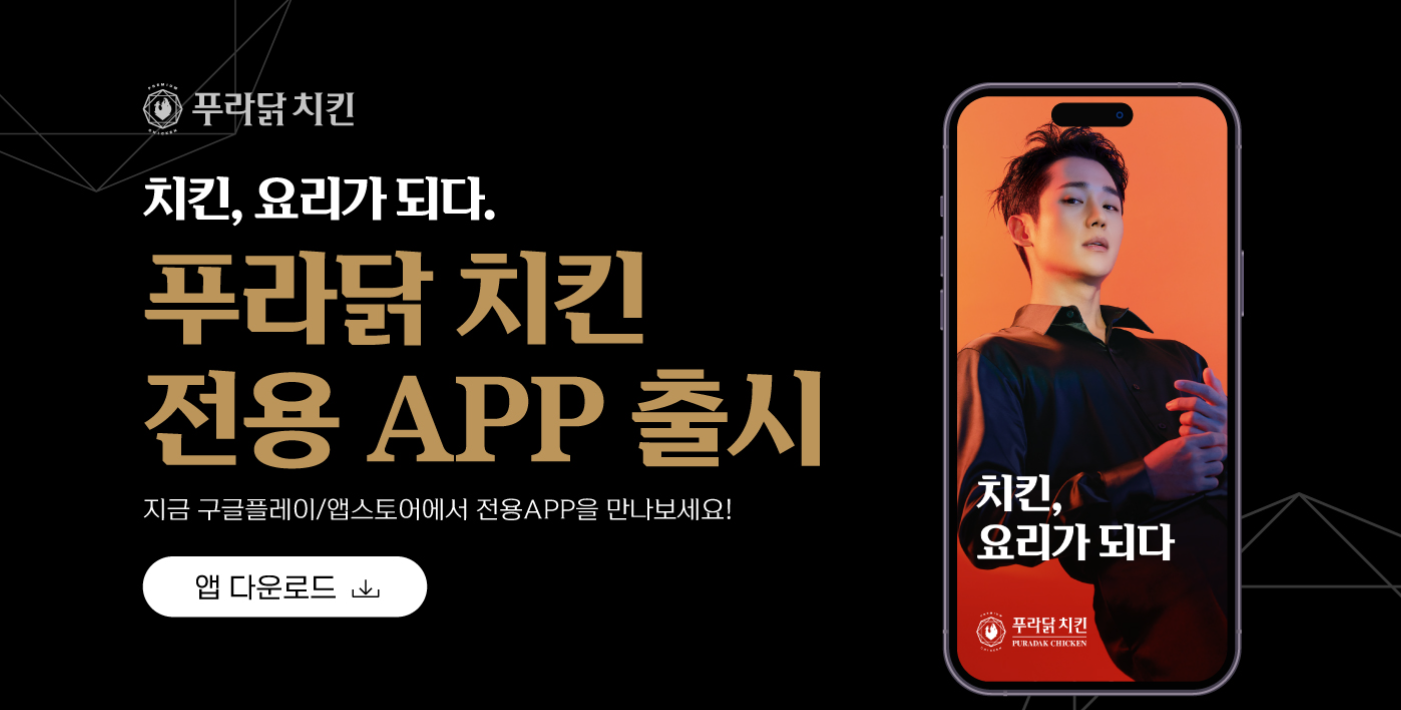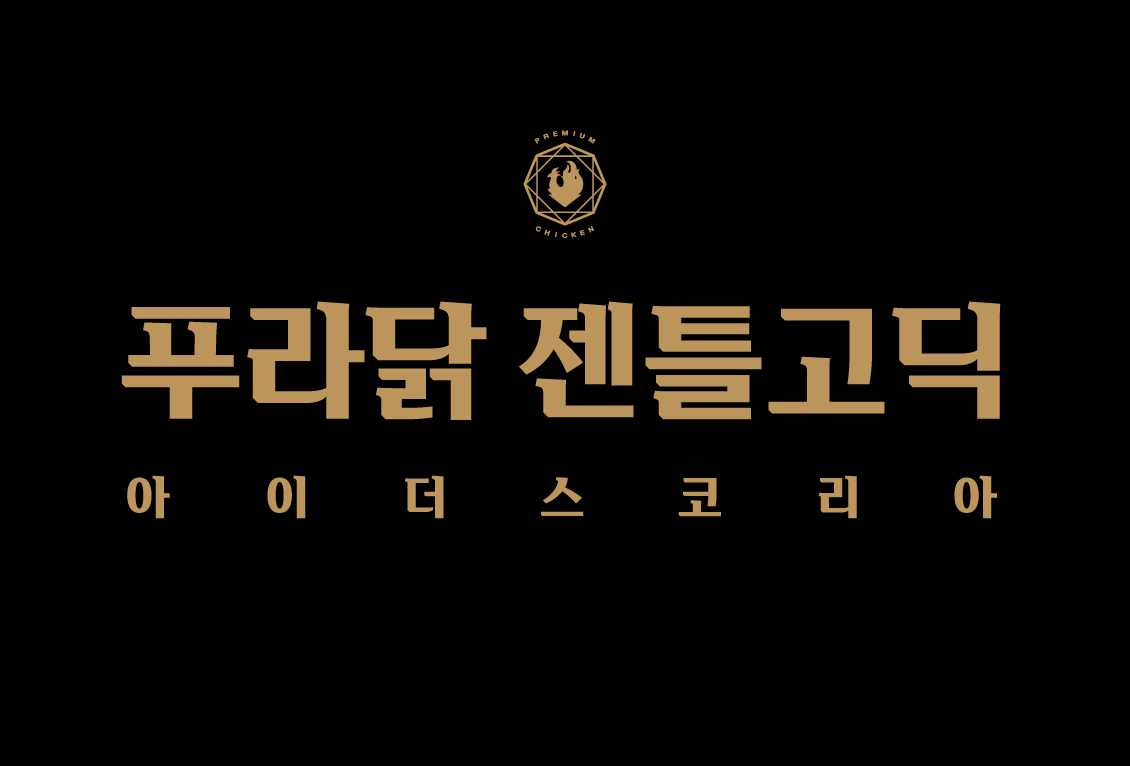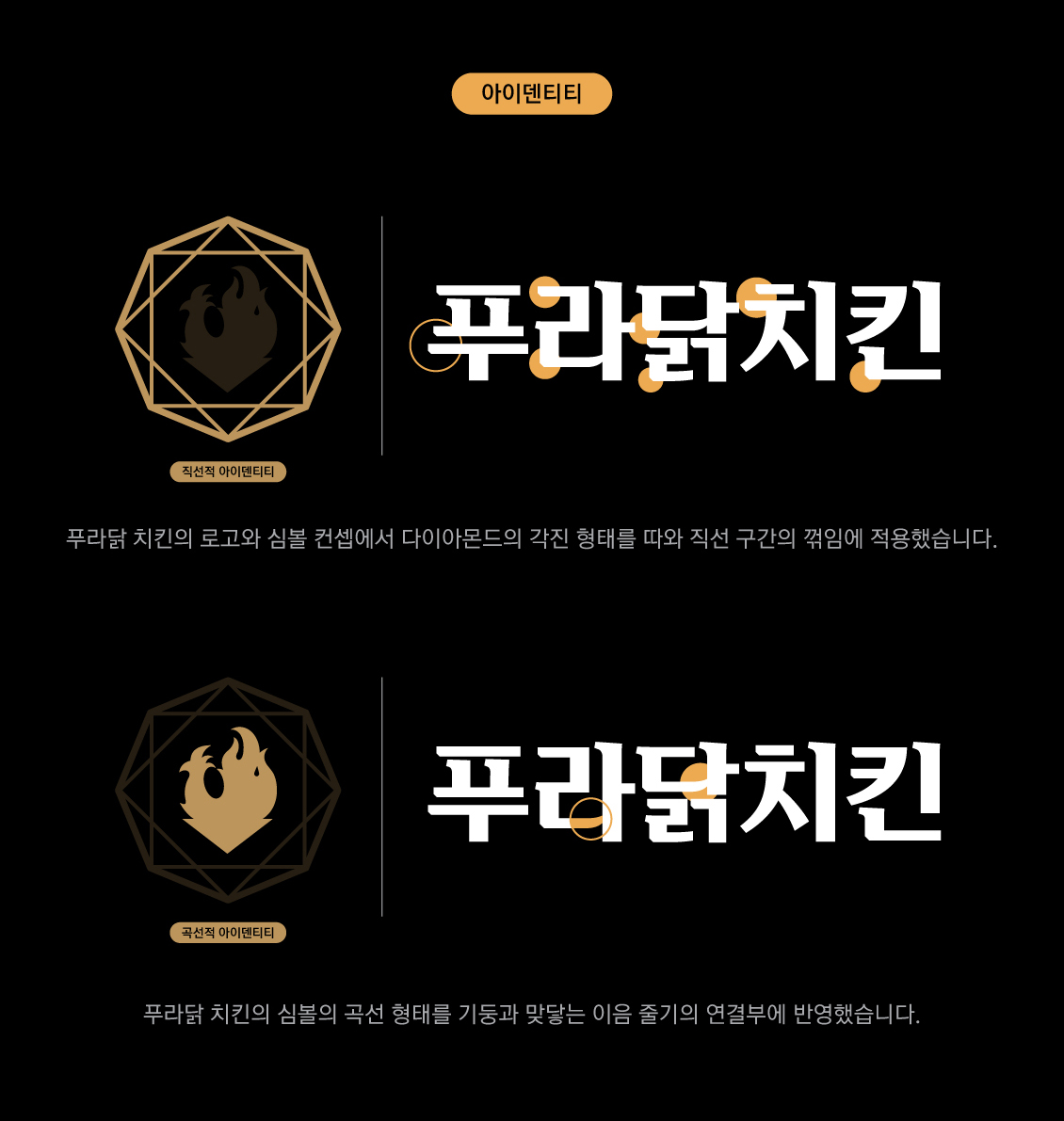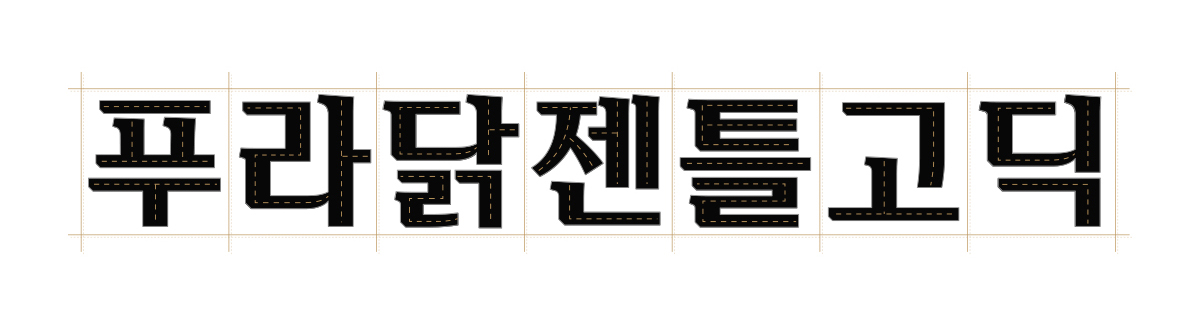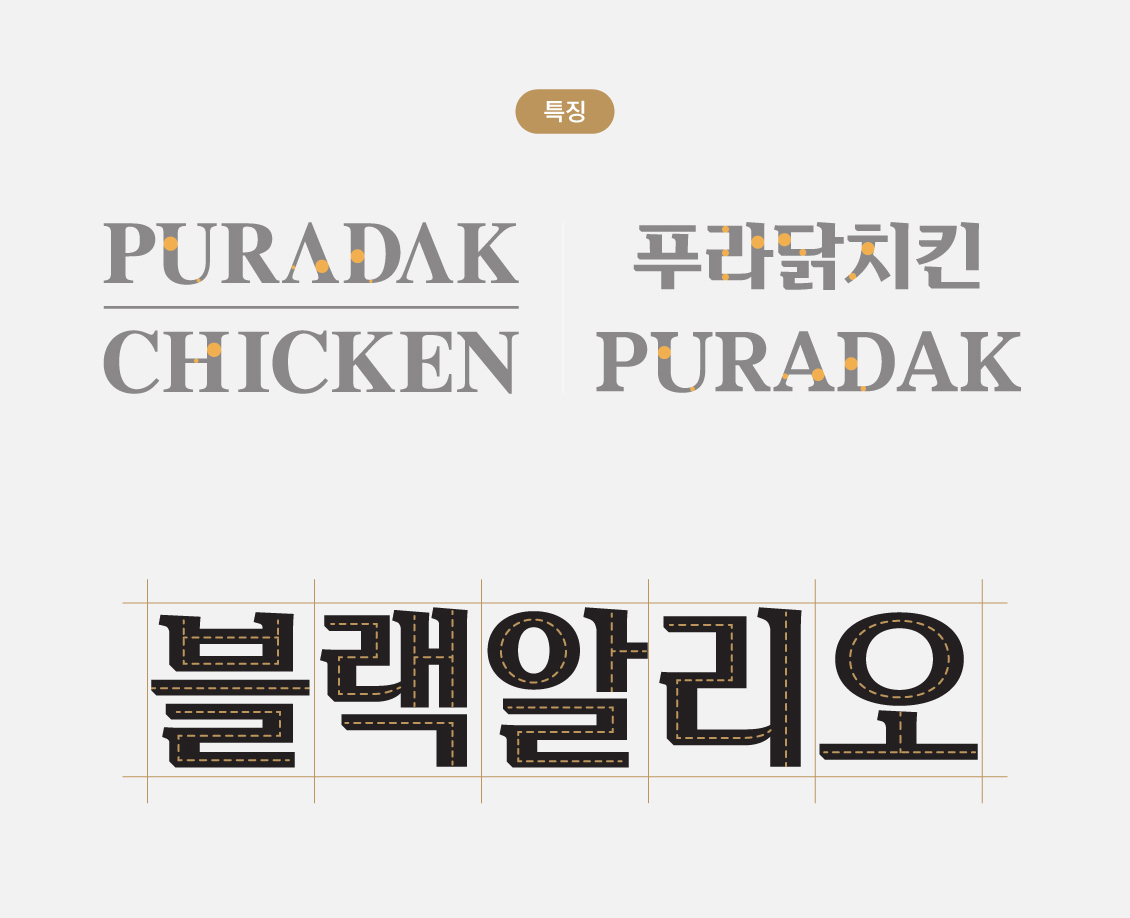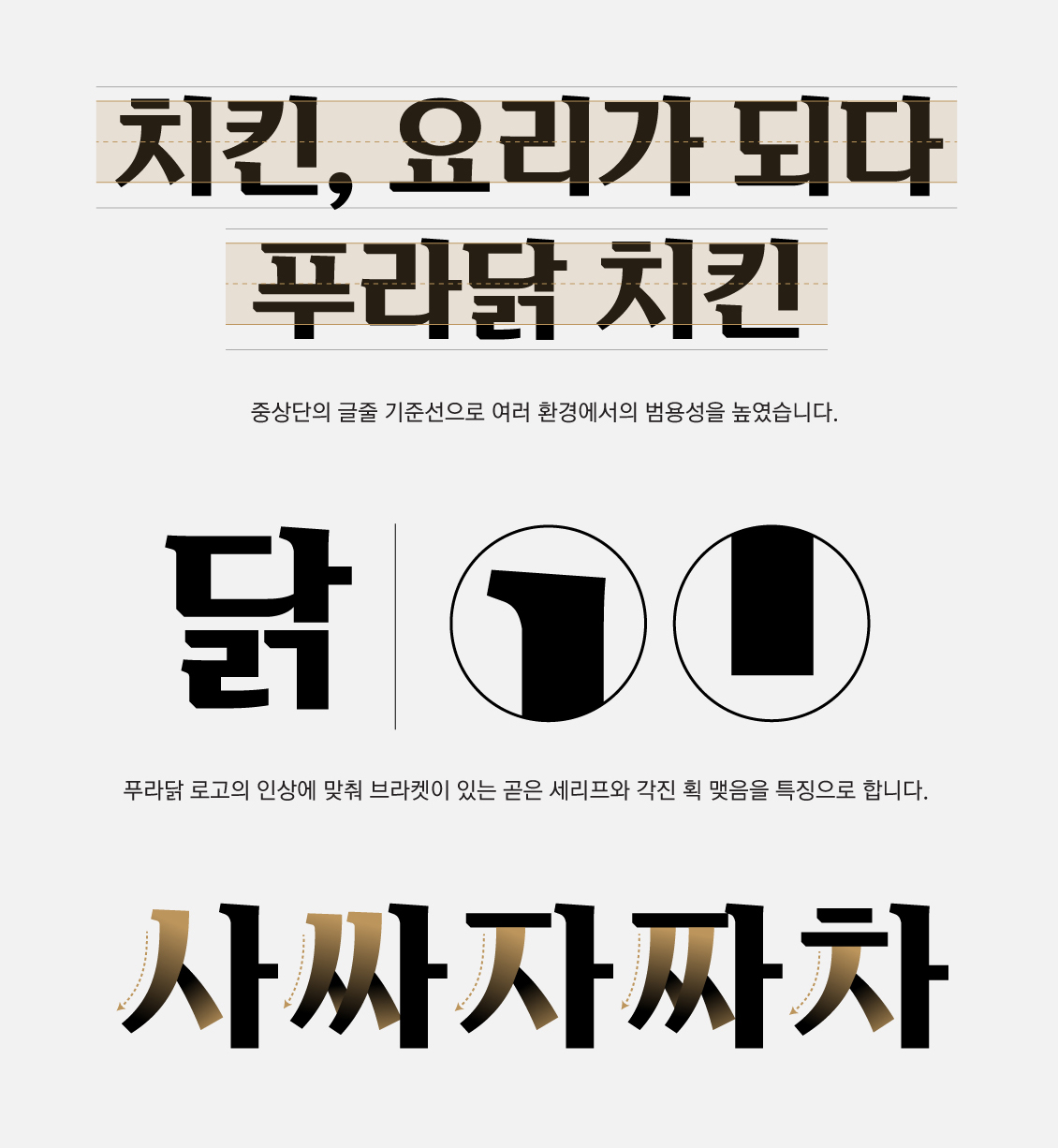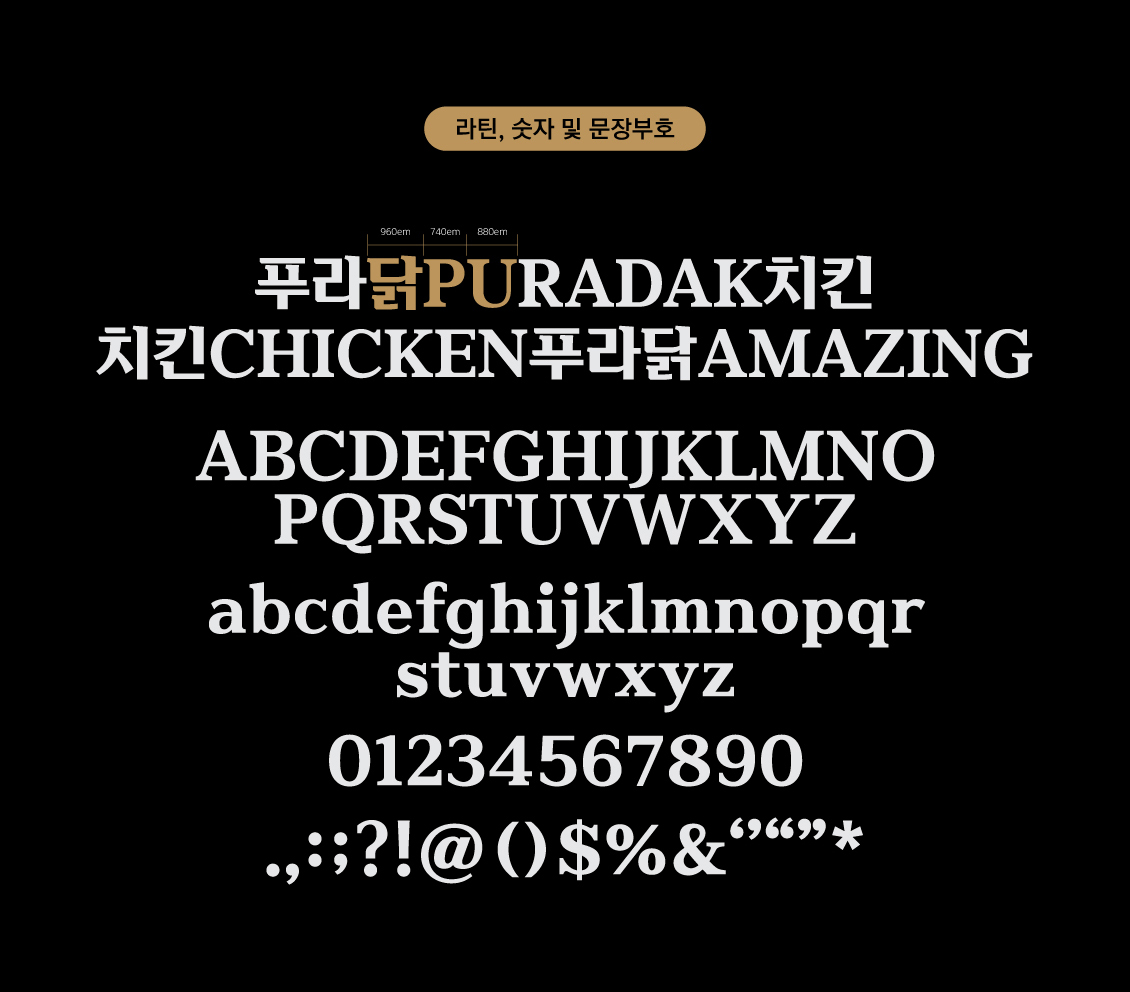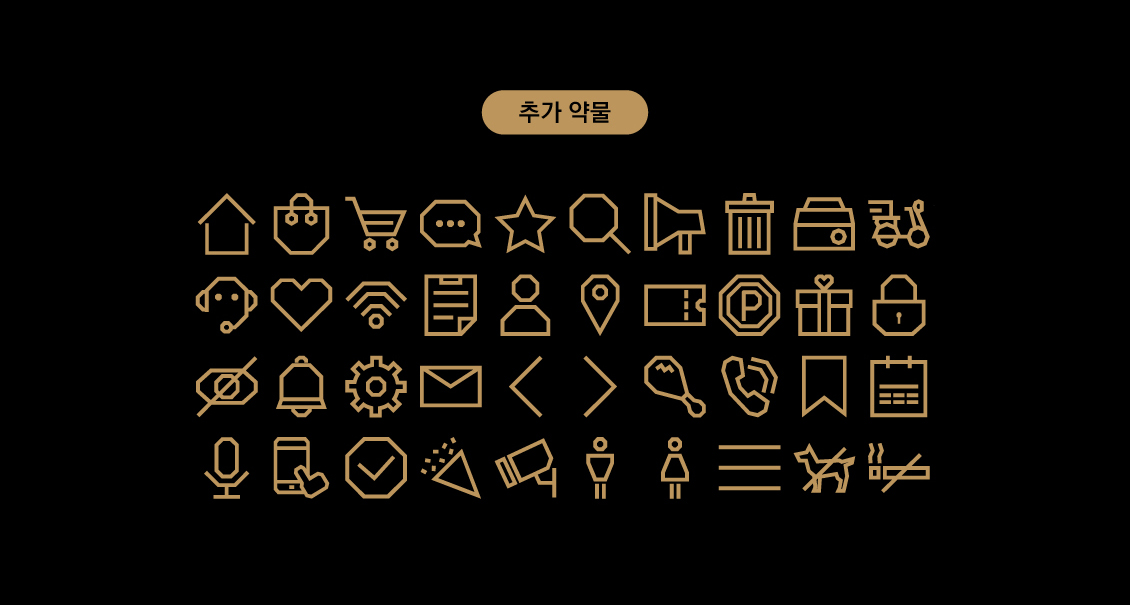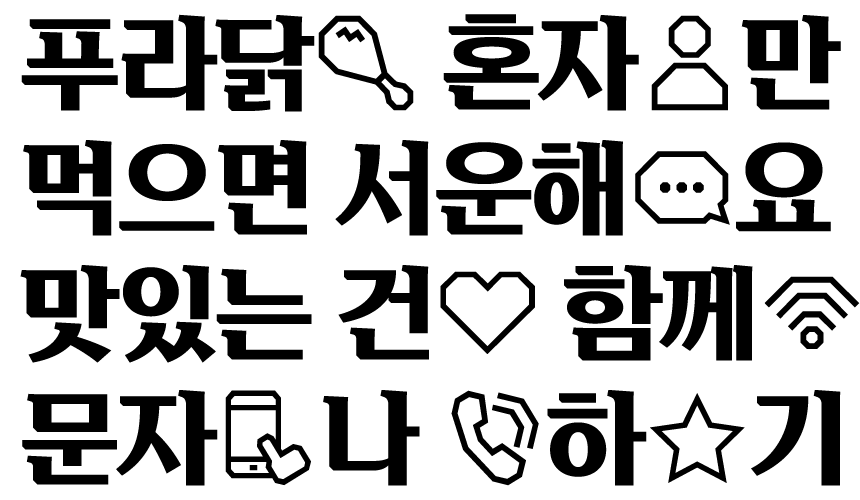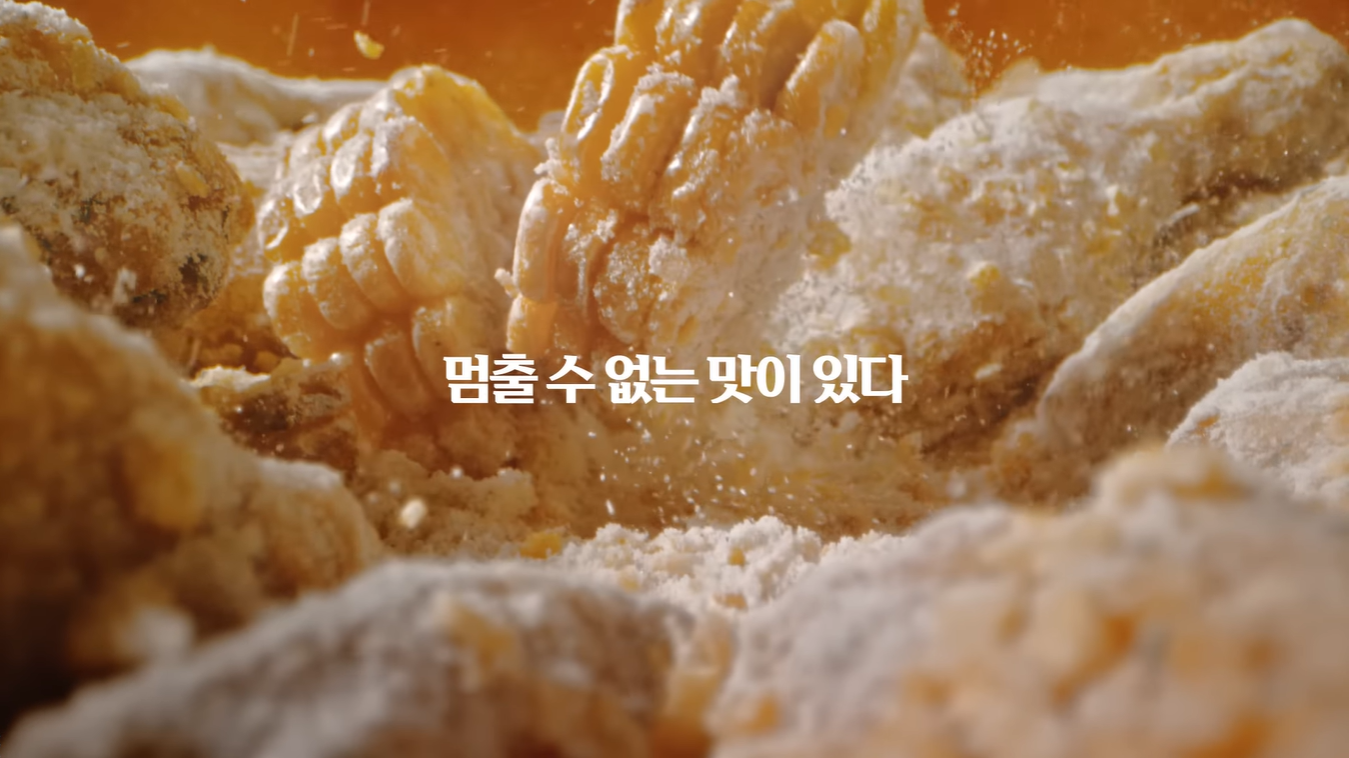
치킨, 요리가 되다.
이 카피를 보면 떠오르는 치킨 브랜드가 있죠🤔 PURA(순수한)+DAK(닭)이라는 두 단어를 조합해 순수하고 정직하게 최고의 치킨 요리를 선사하겠다는 의미를 담고 있는 푸라닭 치킨(아이더스 코리아) 전용서체로 제작했던 「푸라닭 젠틀 고딕」을 소개합니다. 고급스럽고 차별화된 푸라닭 치킨 브랜드만의 개성을 살려 제작한 제목용 전용서체입니다.
로고와 심볼, 아이덴티티를 그대로
푸라닭 젠틀 고딕은 기존 푸라닭 치킨의 아이덴티티인 로고, 심볼과 어우러질 수 있는 서체로 제작하게 되었습니다.
푸라닭 치킨 로고의 다이아몬드 모양 각진 형태를 모티브로 한 곧고 단단한 골격과 세리프, 심볼의 닭 형상에서 착안한 부드러운 곡선과 굴곡을 디자인에 적용했습니다.
고급스럽고 개성 있는 디자인
단순히 치킨을 넘어 요리의 가치를 담아내겠다는 푸라닭 치킨의 브랜드 이념에 맞게 푸라닭만의 고급스러운 느낌과 개성 강한 인상을 살려 제작한 제목용 서체입니다.
기존 로고 타이틀에서의 특징을 유지하며 글자 획의 폭 대비를 줄여 활용성을 늘렸습니다. 고딕 서체와 유사한 골격으로 곧은 세리프와 단단한 인상이 살도록 디자인했습니다.
가로 세로 획의 굵기 대비에 맞춰 균형 있게 비스듬히 뻗어나가는 자소 형태를 디자인했습니다.
라틴, 숫자 및 문장 부호 디자인 또한 한글 서체의 특징을 그대로 살려 디자인했습니다. 한글과 혼용 시 자연스럽게 쓸 수 있도록 골격과 자폭, 굵기 등을 보정했습니다.
푸라닭 치킨과도 잘 어울리고 재미있게 활용할 수 있는 픽토그램 40종을 추가 약물로 제작했습니다. OTF 폰트 파일을 다운로드하면 포토샵, 일러스트레이터 등 어도비 프로그램 -문자 - [글리프] 패널에서 선택하여 사용할 수 있어요!
푸라닭 젠틀 고딕의 활용
푸라닭 치킨 전용서체는 TV 광고, 유튜브, 홍보 배너 등 다양한 매체에서 활발히 활용되고 있으며, 푸라닭만의 스타일과 컨셉을 표현하는데 큰 역할을 하고 있습니다.